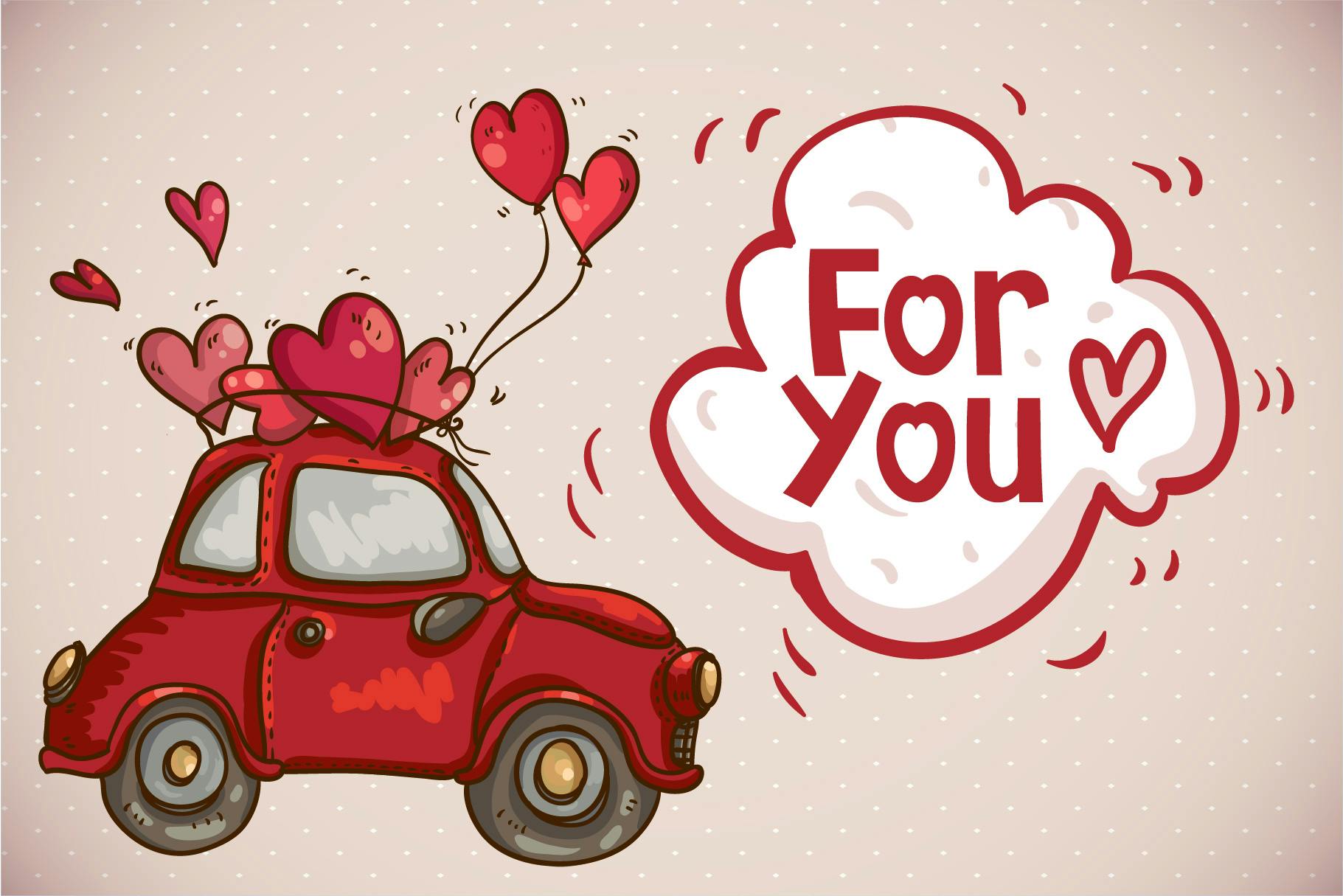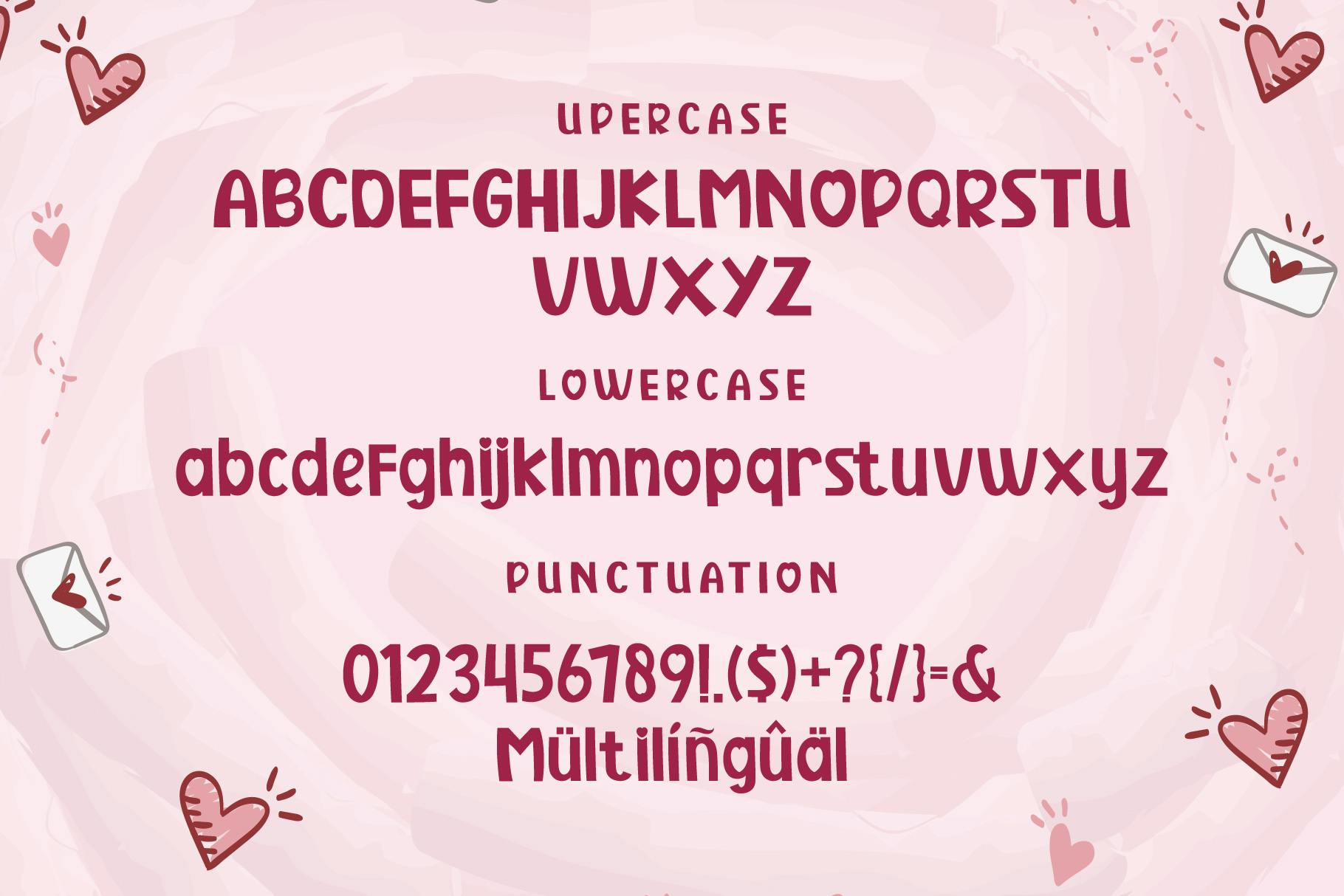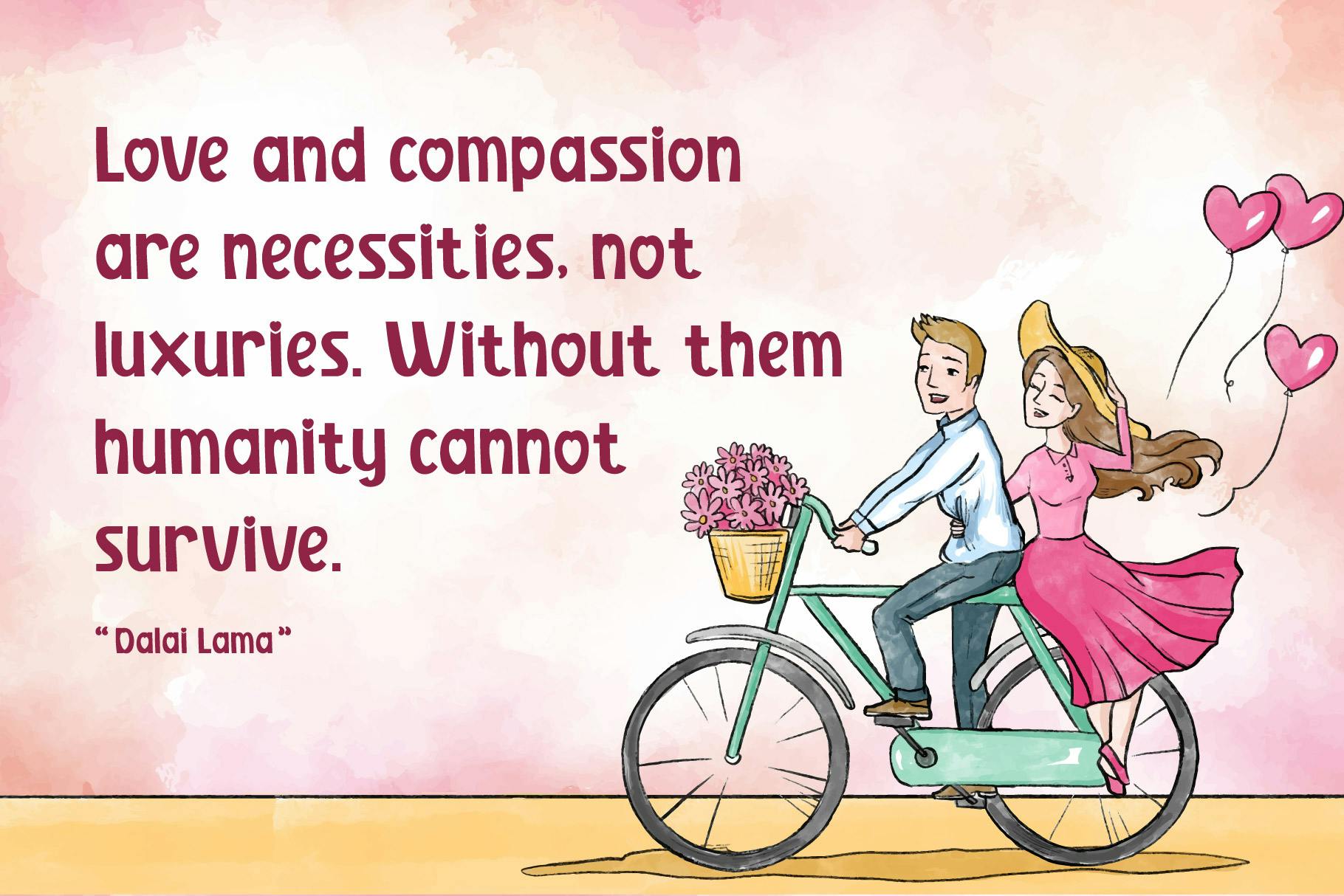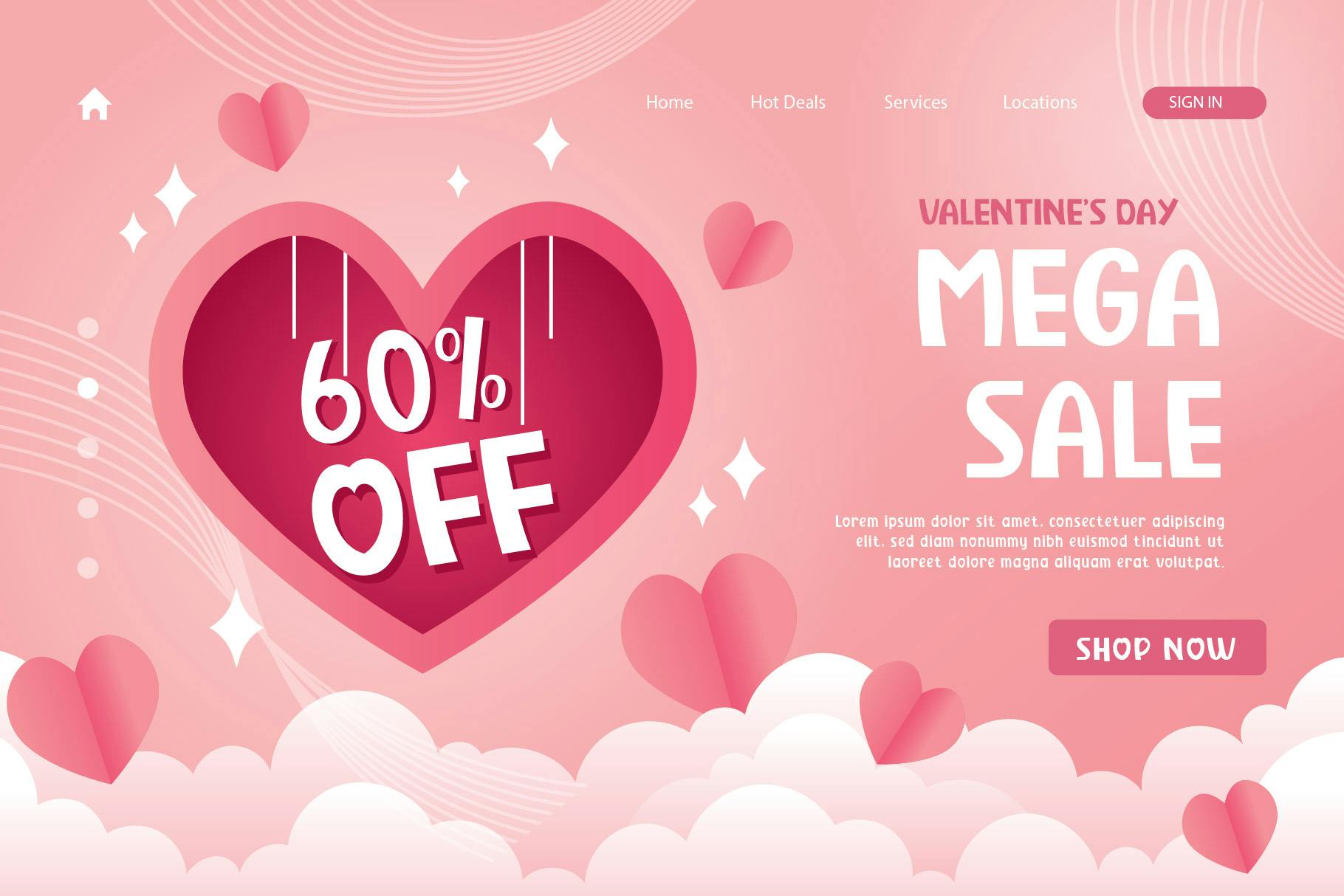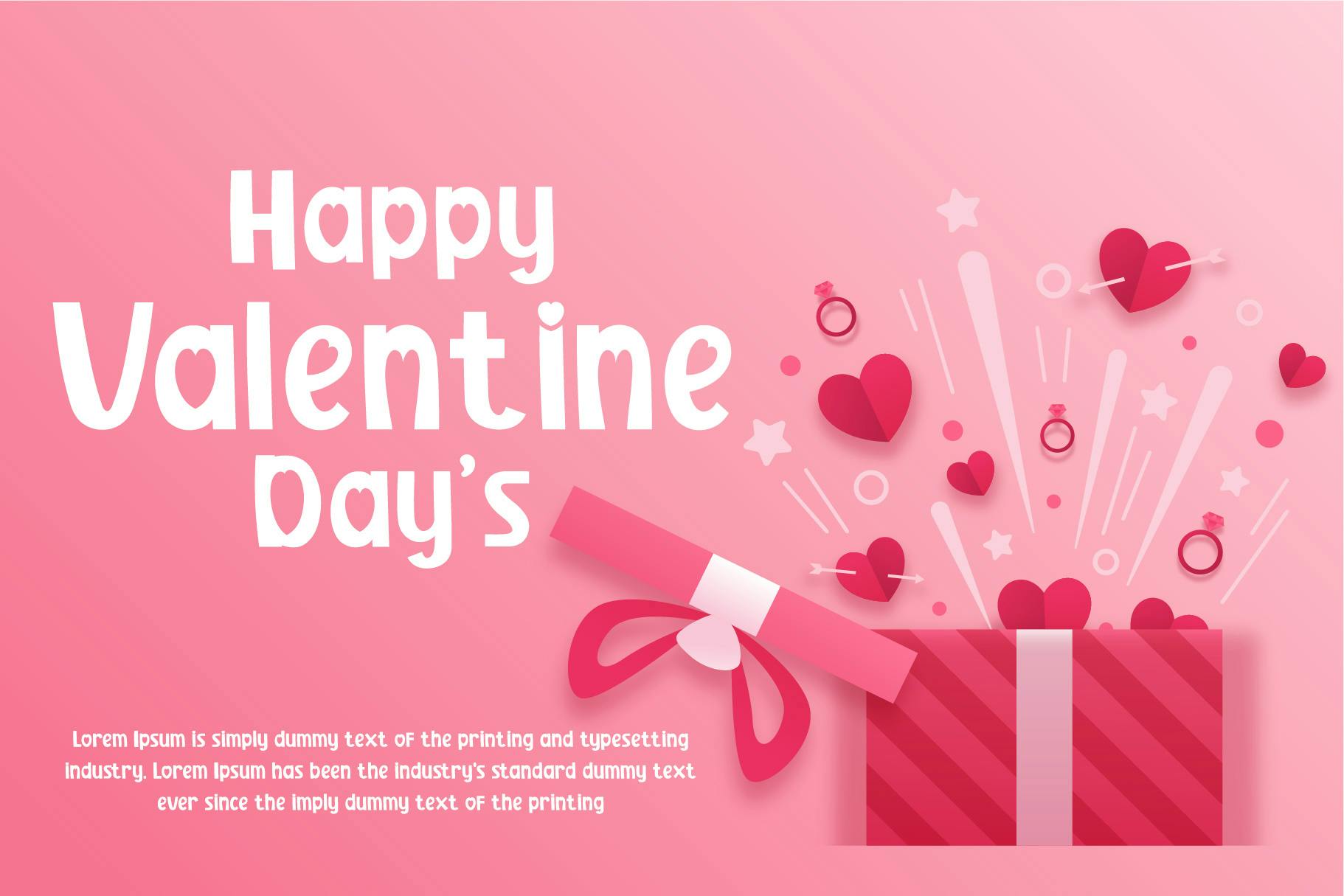
فونت Rolling Love یک فونت نمایش دلنشین است. این فونت میتواند برای محصولاتی مانند صنایع دستی، بستهبندی محصولات، نقلقولها، طراحی محصولات، آثار هنری، برچسبها، عکاسی، واترمارکها، لوگو و برندینگ استفاده شود.